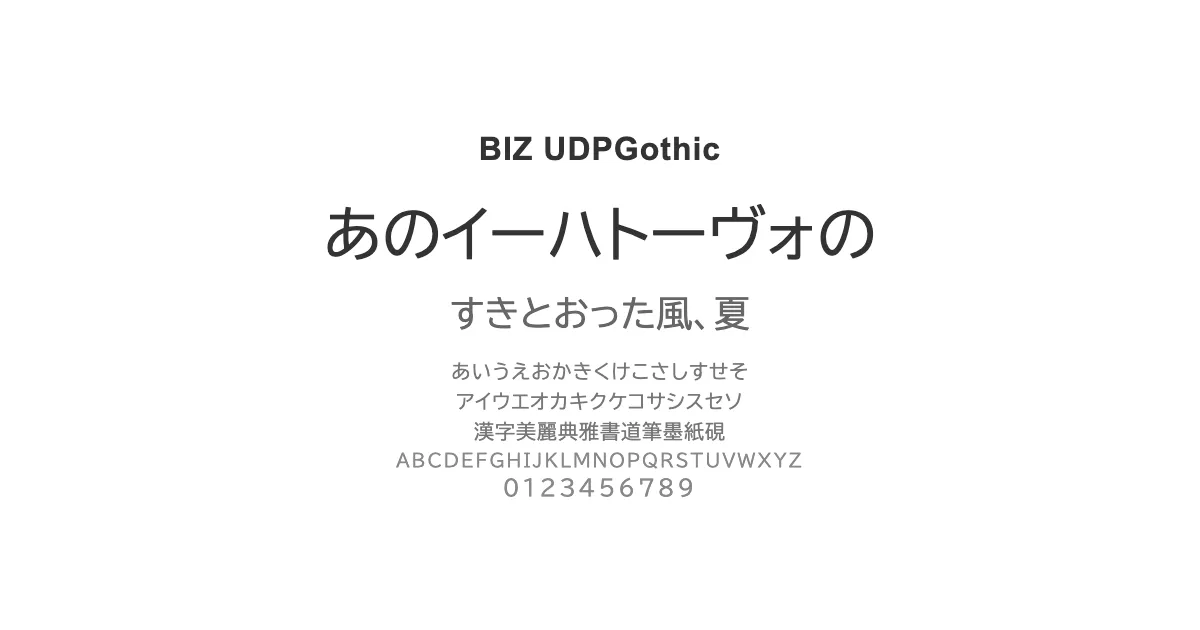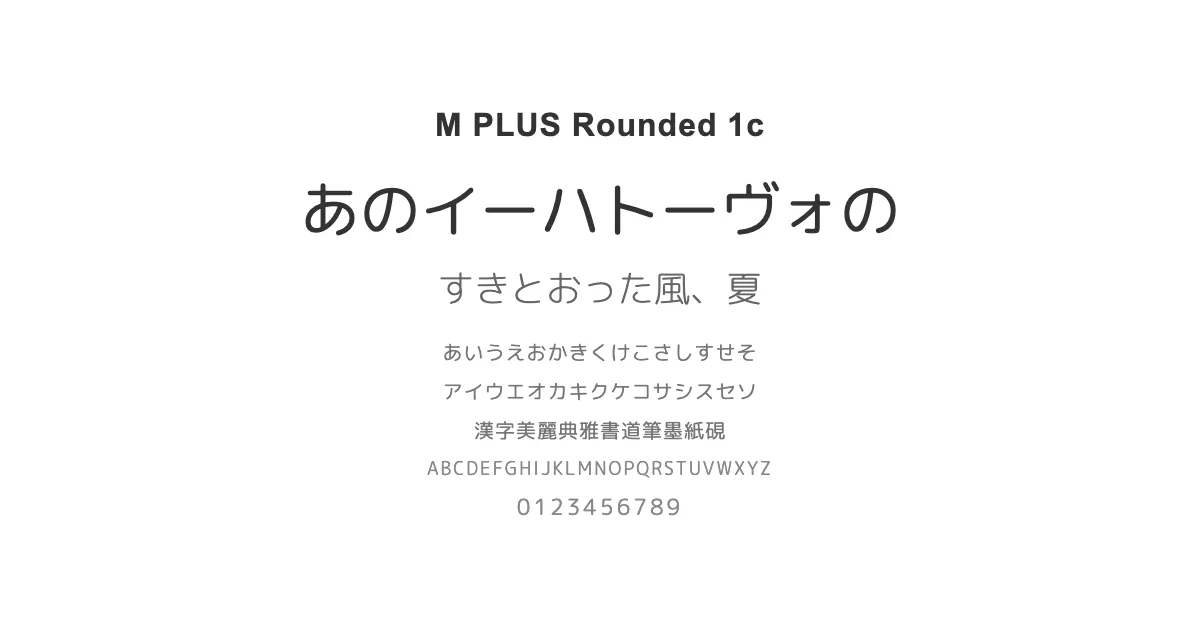
丸みを帯びて、漢字が細めにデザインされている明朝体フォント。部分的に墨のにじみや墨だまりがあり、伝統的で上品な印象。
本文に使用することを想定したスタンダードで可読性の高いゴシック体フォント。文字サイズが小さくてもつぶれにくい。
太めの油性マジックで書いたような、Google Fontsの日本語の中では数少ない手書きフォント。見出しやキャッチコピーに。
手書きのような文字と活字らしさも感じるフォント。ボールペンで書いたような文字で、可読性・視認性にも優れている。
より多くの人に読みやすく分かりやすいように設計されたユニバーサルデザインのゴシック体フォント。シンプルで柔軟性がある。
細ペンで描いたようなかわいらしい字体の手書き風フォント。等幅で縦書きでも使え、読みやすさも兼ね備えている。
丸みを帯びたフォルムが特徴的で、親しみやすい印象を与える丸ゴシック体フォント。かわいらしさや楽しさを感じさせる。
明朝体風で文字の先端に丸い「うろこ」がかわいらしいモダンな印象のフォント。丸いドットの装飾によってポップでかわいらしい。
明朝体風で文字の先端に丸い「うろこ」がかわいらしいユニークなデザインフォント。「はね」や「はらい」の部分に丸いドット。
エッジが丸く、とても上品なオールドスタイルの明朝体フォント。柔らかな筆のタッチと、なめらかなで上品な曲線が特徴。